如何为您的品牌挑选合适的字体
想一想您童年时的某个品牌,想到它就会让您想起人生中的那段时光。这个品牌还在吗?或许它还在,然而令人惊讶的是,很多我们最喜欢的品牌都在挣扎着与它们所服务的群体一起发展。
为了保持影响力,品牌必须经常通过新产品研发、新的视觉审美以及新的广告宣传来重新塑造自己。在任何一种情况下,公司都需要选择品牌字体以传达有凝聚力的形象、并与忠实的客户受众产生共鸣。对于许多品牌管理者来说,这个过程可能是一个相当大的挑战。
那么,什么是“品牌字体”?
在各个行业中,有的人推崇它,有的人却对它视而不见。即便是在蒙纳 (Monotype),我们也会使用显著的标签对新发布的产品推崇备至,比如“品牌设计必备字体”或“根据品牌设计的需求精心定制”。
当然,对于做出字体决定的品牌来说,“品牌字体”的真正含义远比想象中的要复杂得多,也更个人化。
功能第一,形式第二
“‘品牌字体’可以说不是术语”,蒙纳公司字体设计总监 Steve Matteson 说,“所有的字体都有自己的声音,坚持使用这种声音是品牌自我表达的关键。”
换句话说,品牌字体的质量并不取决于它的外观,而是取决于如何使用它。记住,字体几乎可以在品牌所接触的所有印刷材料和数字展示上使用。对于一些公司来说,这些接触点可能有很多。因此,合适的品牌字体可以满足您所需要的多样性用途,从而实现在每个接触点上都能传达出一致的品牌内涵。
蒙纳公司的设计师 Malou Verlomme 说:“对于大公司来说,品牌会有很多的交流、渠道和接触点。最棘手的问题是在维持品牌认知度,同时保持品牌的牌功能性、可读性和持久性的强大标识之间找到适当的平衡。”
从这个角度来看,我们可以在选择品牌字体时为品牌建立宽泛参数。“一款‘好的’品牌字体会有一个精心制作的、大的字体家族,为您的品牌提供丰富的选项。” Matteson 说,“这样您就能在不同的语言和环境中有效地表达您的品牌。”
在实践中,这意味着要寻找这样一款字体家族:它包含各种不同的字重(粗细)和样式;支持客户所使用的语言;为您的设计团队配备所需要的功能,以创建独特、有吸引力的可视化对象。
“随着越来越多的品牌走向全球,涵盖多种语言的字体也变得越来越重要。” Verlomme 表示,“但当品牌来找我们时,他们并不总是这么想。我们通常是以拉丁语为主,所以最好从一开始就强调这一点。
外观也很重要
这并不是说通用字体能成为很好的品牌选择仅仅是因为这个字体家族包含了数千种字形。事实上,选择或创造一种独特、耐用的设计是品牌需要做出的最重要且最具挑战性的选择之一。
虽然评估字体的功能相当简单,但是设计选择就要复杂得多。
“我遇到的一个最常见的问题是,‘徽标(logo)和文字商标(wordmark)怎么办?’” Matteson 说,“品牌担心的是如果改变字体就不得不改变品牌本身。在这种情况下,我们可以引导品牌找到一种可行的解决方案:
要么选择一种与品牌接近的徽标(logo)或文字商标(wordmark),要么找到一种与之相匹配的字体。
潮流是要考虑的另一个因素。“在‘好’和‘坏’之间要把握好界限。” Matteson 说。举个例子来说,他和韦尔洛姆都注意到现今的几何无衬线体非常流行。这些字体的经典、现代气息唤起了人们的一种怀旧情节。在供许多公司使用时,这些字体的设计也不够典型,不过在各种数字和印刷环境中使用却足够灵活。
“几何衬线体是相当可靠的,它对比度低,而且可以跟各种图形一起使用。” Verlomme 说,“字体将会与各种不同的背景、图标或者其他字体放在一起。所以品牌想要的是简洁、清晰但仍可识别的字体,这样不至于喧宾夺主。”
“有时候,当看到摘要我们就会想,‘啊,不要再用几何衬线体了!’,但是他们的受欢迎程度是可以理解的。
确定您的身份,然后拥有它
然而,这确实提出了一个令人苦恼的问题:是随大流?还是采用自己的方式?当今的设计趋势看起来可能很棒,您也可能会羡慕其他品牌使用超酷的字体,但这并不意味着您一定要效仿。
“当大家都在追求同一种字体风格时,您的品牌有可能会迷失方向或者被湮没。” Verlomme 说,“潮流并不一定适用于您的品牌,不要仅仅因为别人都这么做让您感到压力而去追随潮流。”
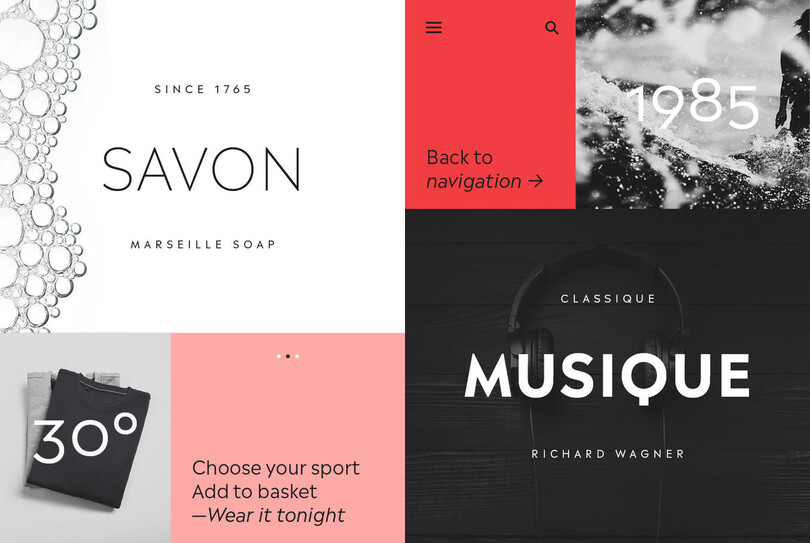
韦尔洛姆最近设计了一款名为Madera的字体,是对流行的几何无衬线体类型新的补充,它为实现有效的品牌塑造提供了一整套包含字重(weight)和样式(style)的工具箱。
当要确定品牌字体的外形时,对话自始至终都贯穿着一个首要的问题:您是谁?为了给品牌选择合适的字体,确定品牌的身份是不可或缺的。
“理想的情况是,一个品牌相信我们能够帮助他们将自己的身份转化为一种恰到好处的字体。” Verlomme 表示,“如果品牌可以通过描述捕捉到的品牌基调、个性和原则来定义自己——全面描绘出他们是谁以及他们想成为什么样子——我们就可以将其转化为排印的形式。”
您想给人留下什么印象?您想要反映什么样的价值观?您想唤起什么样的情感?花时间去诚实地、彻底地评估您所要表达的特征和价值观、甚至于社会因素是如何融入到您的品牌构造的。想想您的客户如何看待您的品牌,以及是如何将其融入到他们的生活当中的。然后把您的评估结果带给您的字体设计师、设计机构或创意团队,找到或设计一种能反映这些品质的字体。
“作为一个品牌,您应该清楚您是谁。” Verlomme 说“不要假装自己是别人。”